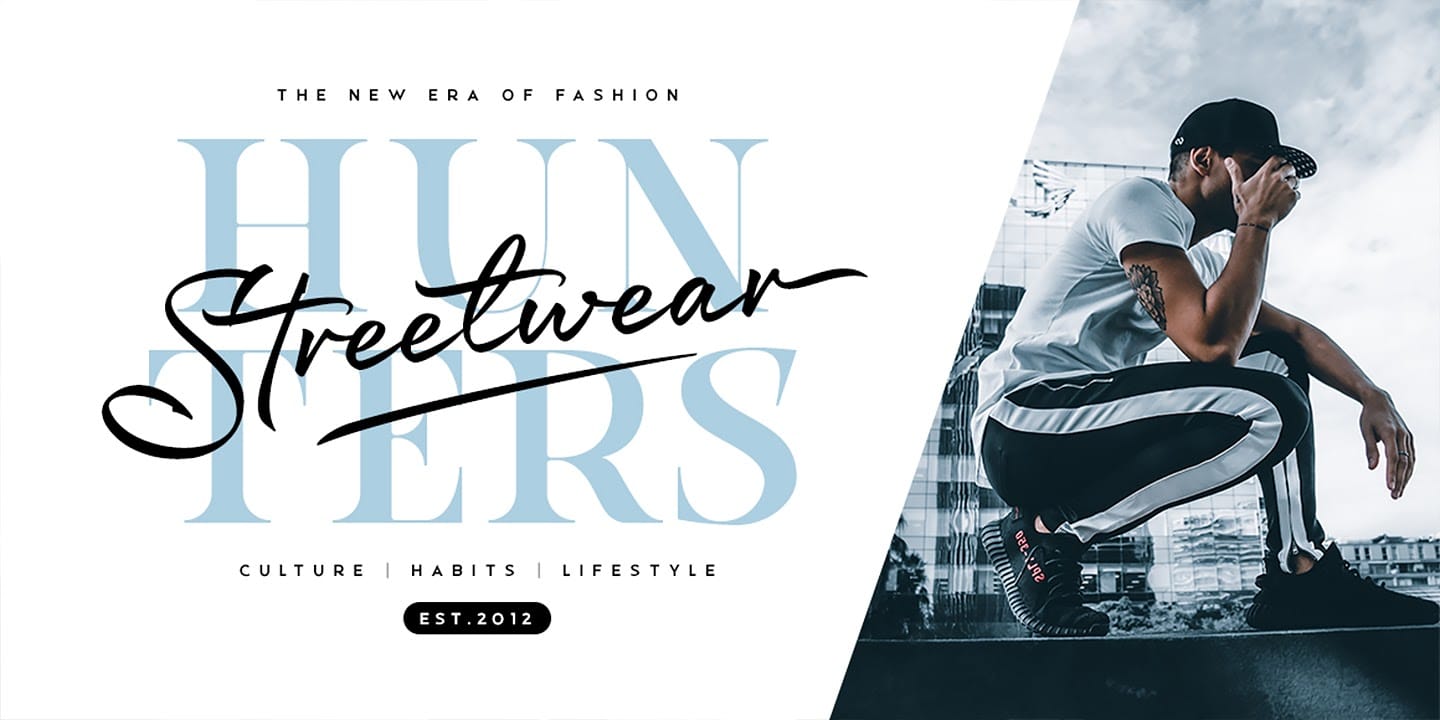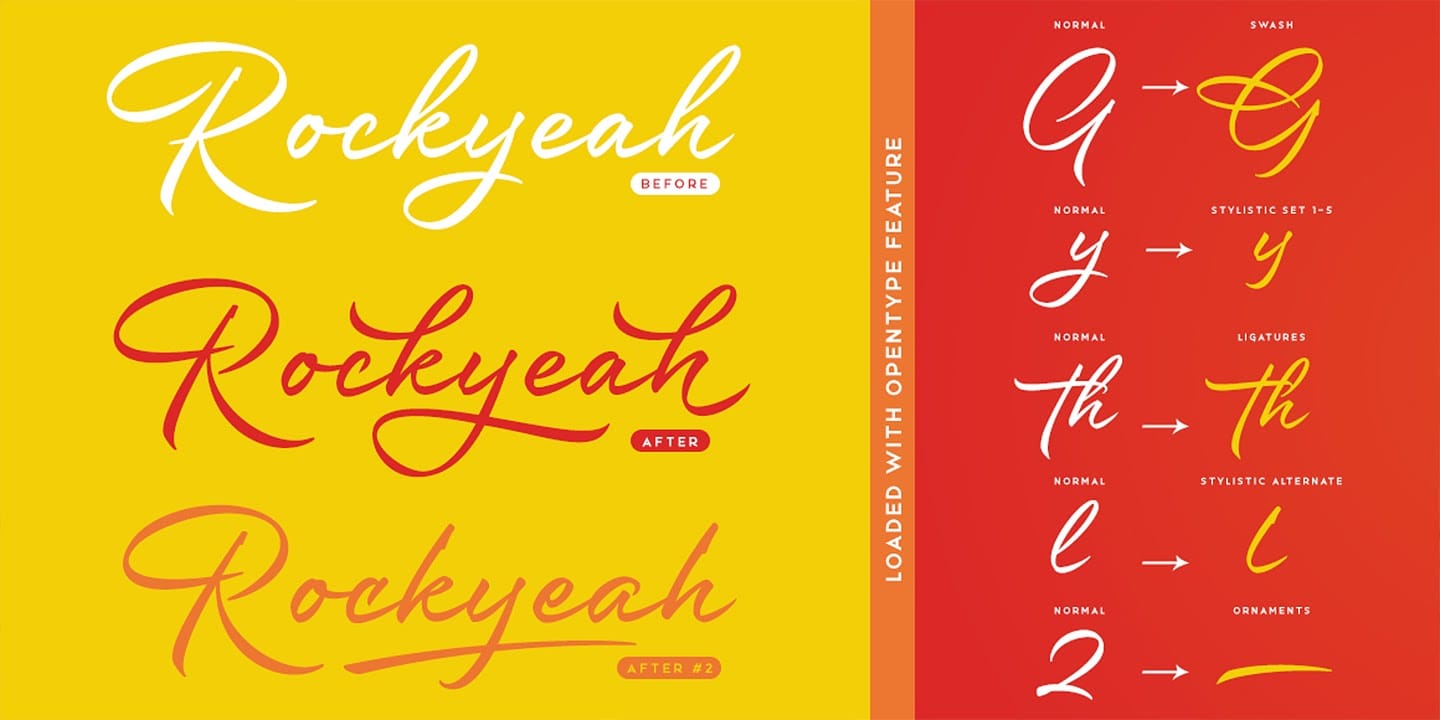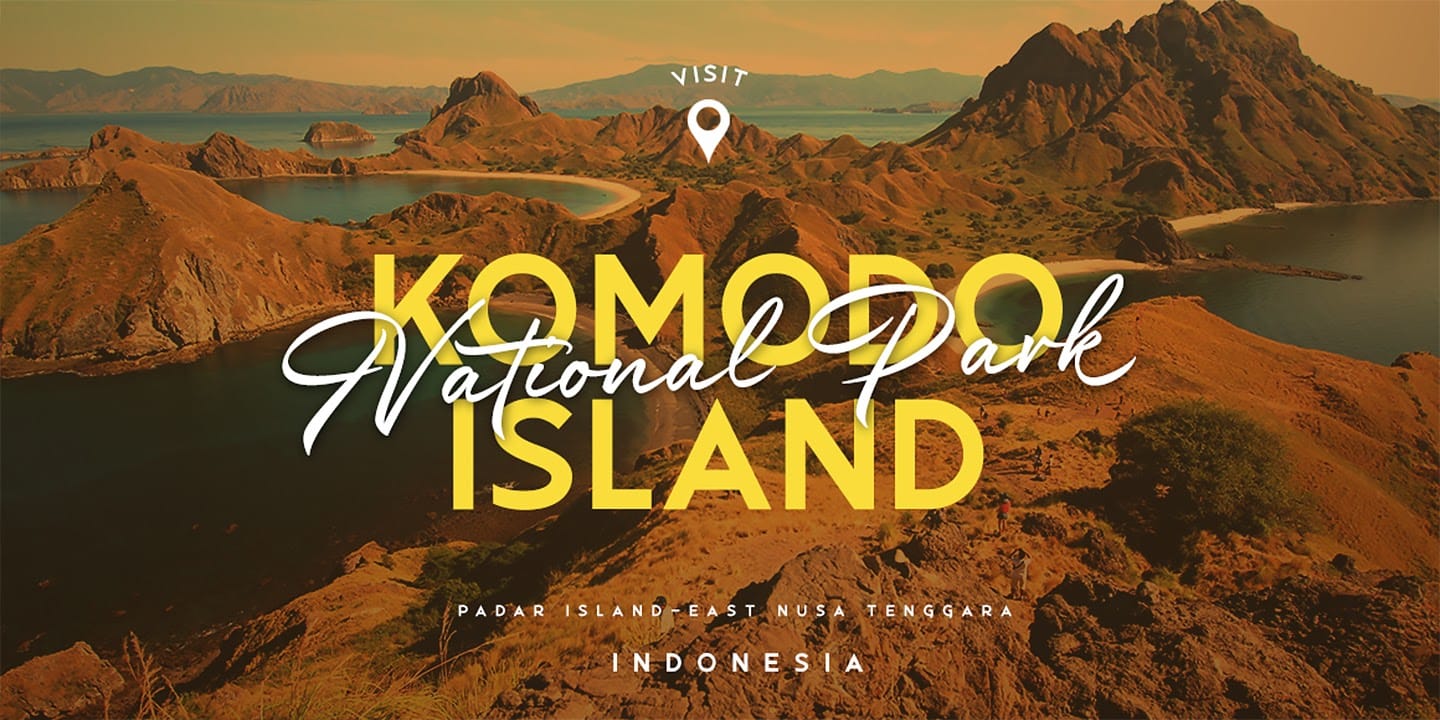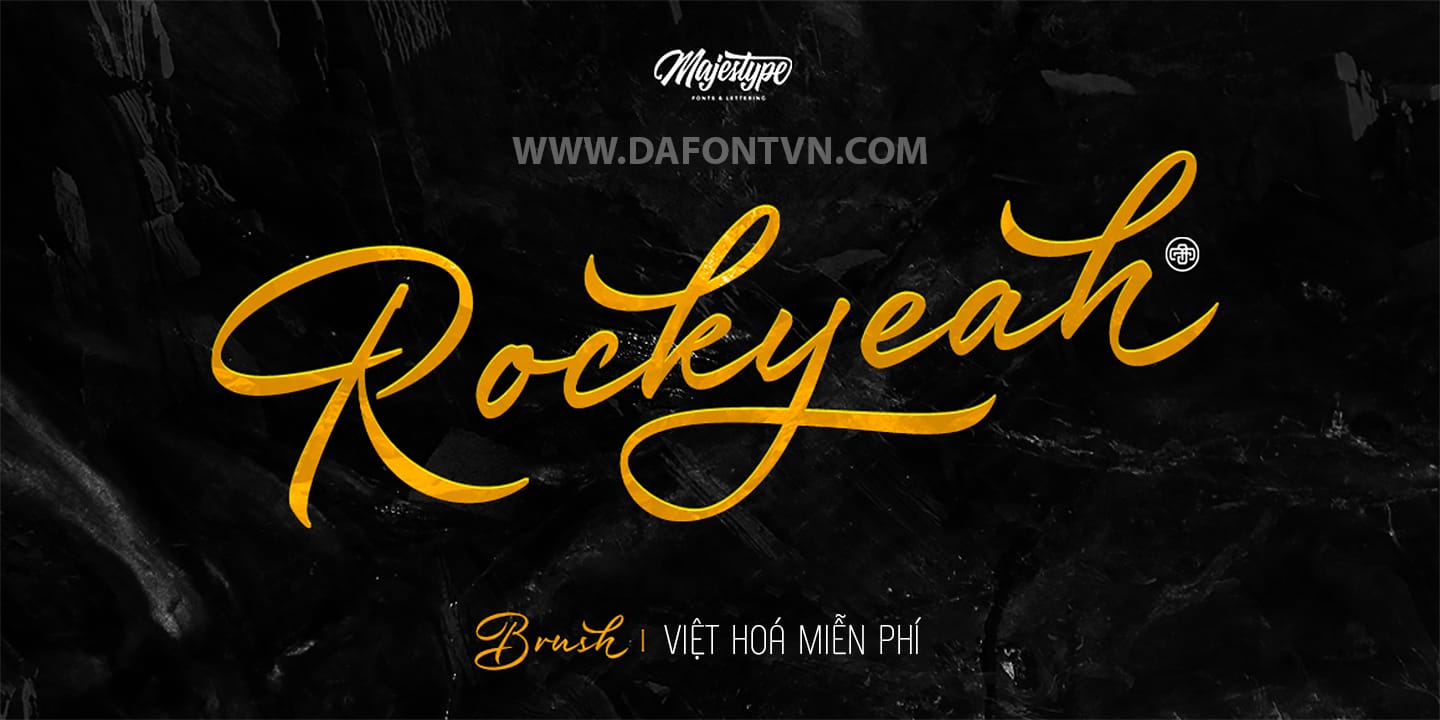
Font Rockyeah Việt Hóa 1 style Rockyeah Brush .
Rockyeah bao gồm 3 font chữ: brush, serif và sans serif.
– Rockyeah Brush được làm bằng bút lông mịn với chuyển động nét vẽ nhanh nhất. Đi kèm với hơn 300 glyphs sẽ cung cấp cho bạn khả năng lớn để chơi với từng nhân vật.
– Rockyeah Serif tập trung vào sự dễ đọc, trang nhã và độc đáo. Với sự kết hợp giữa nét nhạt và nét đậm, serif này sẽ mang lại cảm giác hiện đại cổ điển cho dự án thiết kế của bạn.
– Rockyeah Sans một sans serif hình học tập trung vào tính dễ đọc, rõ ràng và hữu ích cho bất kỳ dự án nào. Đây là cách diễn giải của Rockyeah Serif với cùng chiều cao chữ hoa và nét đậm.